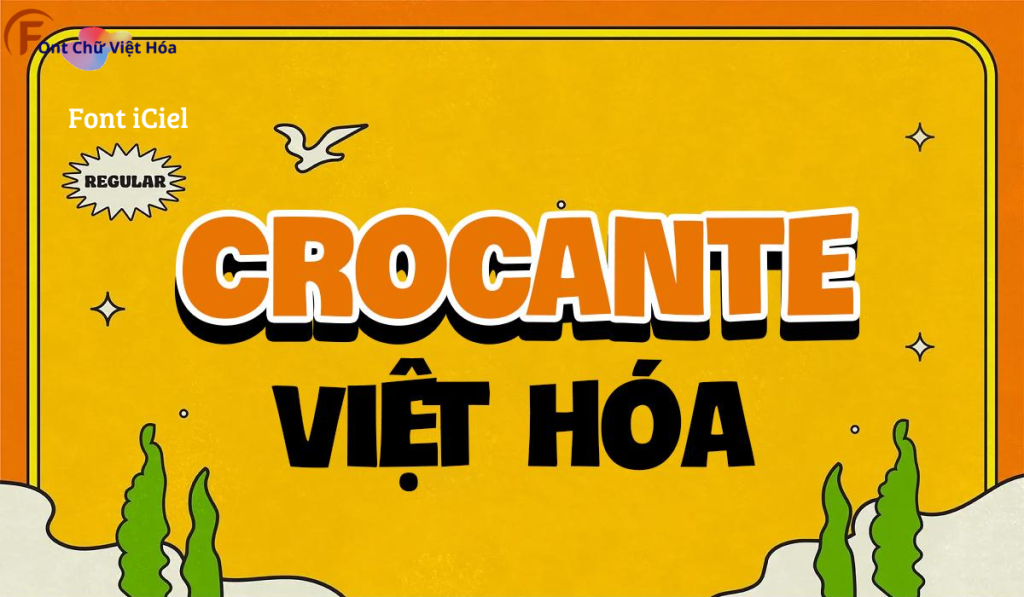
Font iCiel Crocante Việt Hóa
Tác giả: iCiel Crocante
Bộ Font: iCiel
Phân loại: Cá tính, độc đáo
Font iCiel Crocante Việt Hóa, thuộc bộ font iCiel, là font sans-serif cá tính, nổi bật với các nét chữ độc đáo và độ dày đa dạng. Font này có các đường nét mạnh mẽ, dễ đọc, tạo cảm giác sáng tạo và chuyên nghiệp. Font iCiel Crocante Việt Hóa lý tưởng cho các dự án thiết kế như poster, logo, và bao bì sản phẩm. Việc Việt hóa font giúp người dùng dễ dàng tích hợp vào các thiết kế tiếng Việt, mang lại sự tiện lợi và nâng cao tính thẩm mỹ.